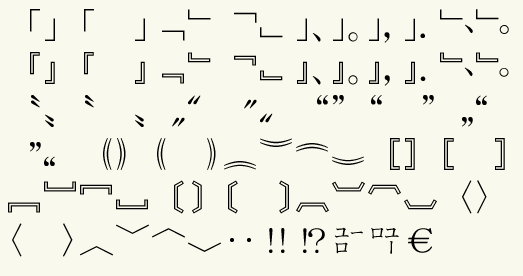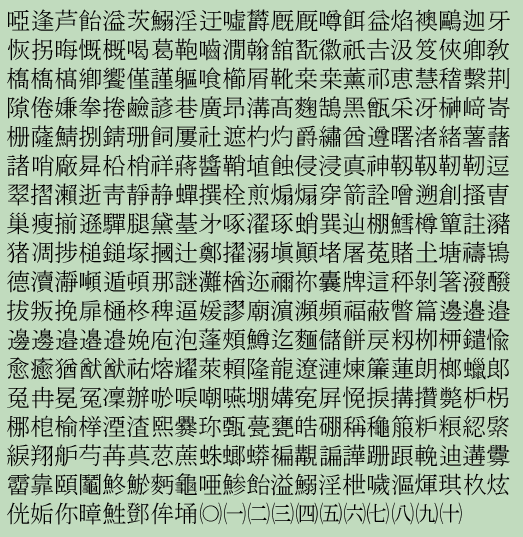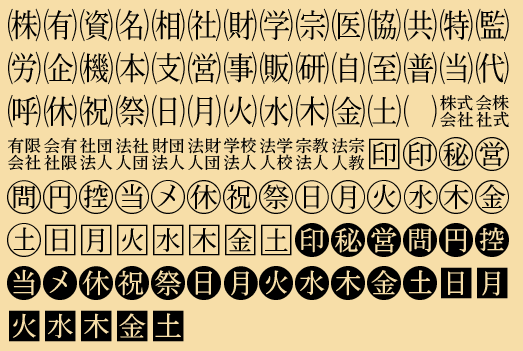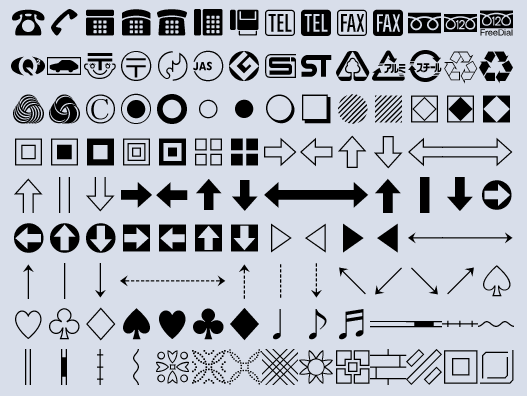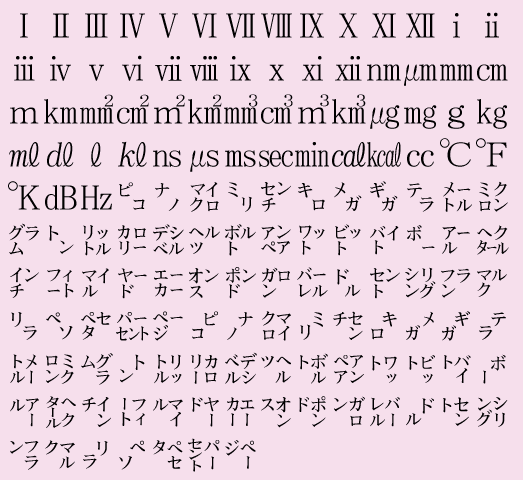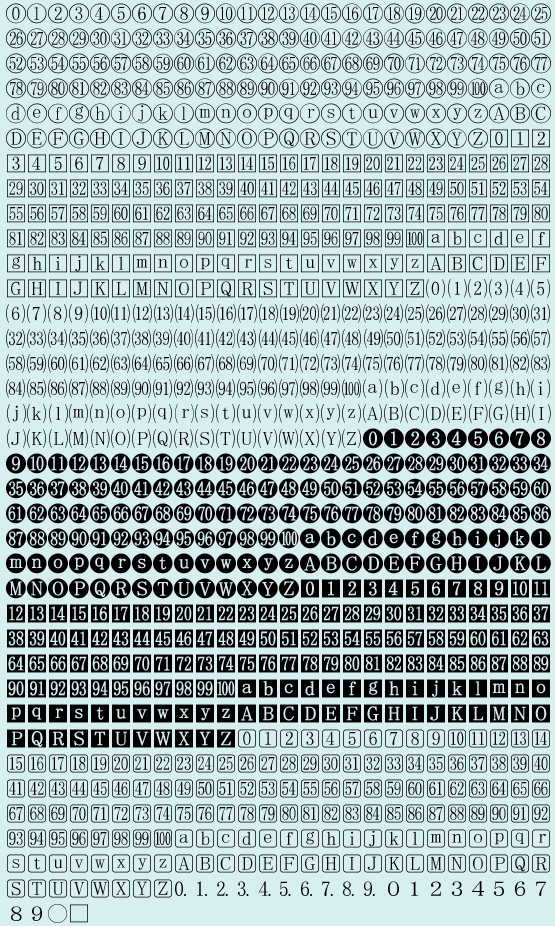
角ゴシック
FE記号ゴシック外字2 (外字1,774文字のみ)
パソコンで表示・印刷出来なかった記号も解決!
本製品は、イーストのパッケージ製品「記号外字1800 V2.5」に収録の角ゴシック体フォントです。Windowsパソコンで入力できない100までの○囲み数字や、白抜き英数字、いろいろな矢印マークや、単位記号、省略文字、人名漢字などを1774文字収録しています。使用頻度の高いMSゴシックと一緒に使用して違和感ないデザインとなっています。
MacintoshDTPで定番となっている「ビブロスフォント外字セット」(記号フォント+漢字フォント)を、Windows標準のTrueTypeフォントでご提供します。名簿や契約書作成、テスト作成などにもご利用いただけます。
FE記号ゴシック外字2 (外字1,774文字のみ)
【外字収録数】1,774文字(記号類1,398文字、漢字376文字)
【収録外字一覧】(明朝体を例にした画像が表示されます)